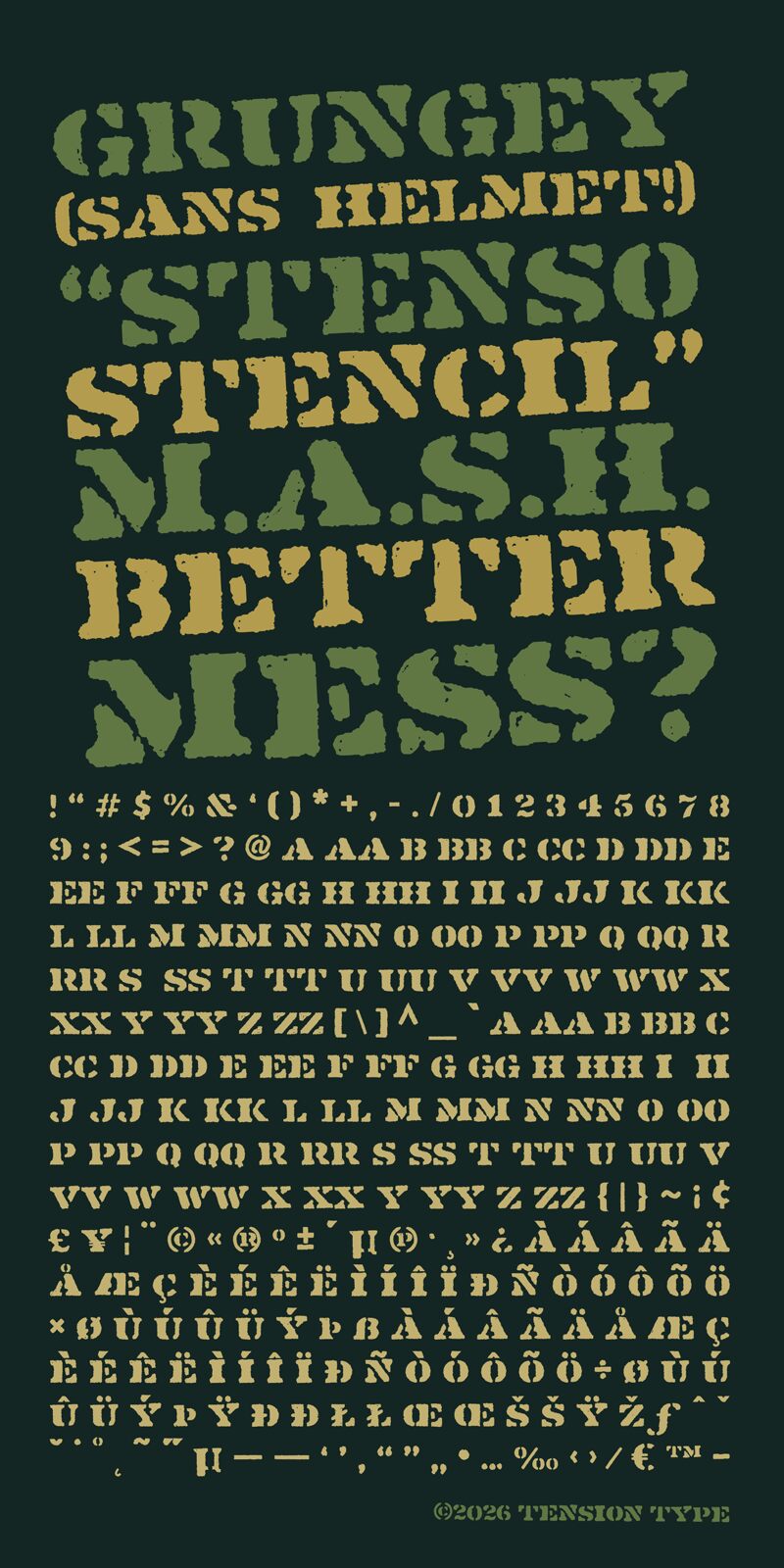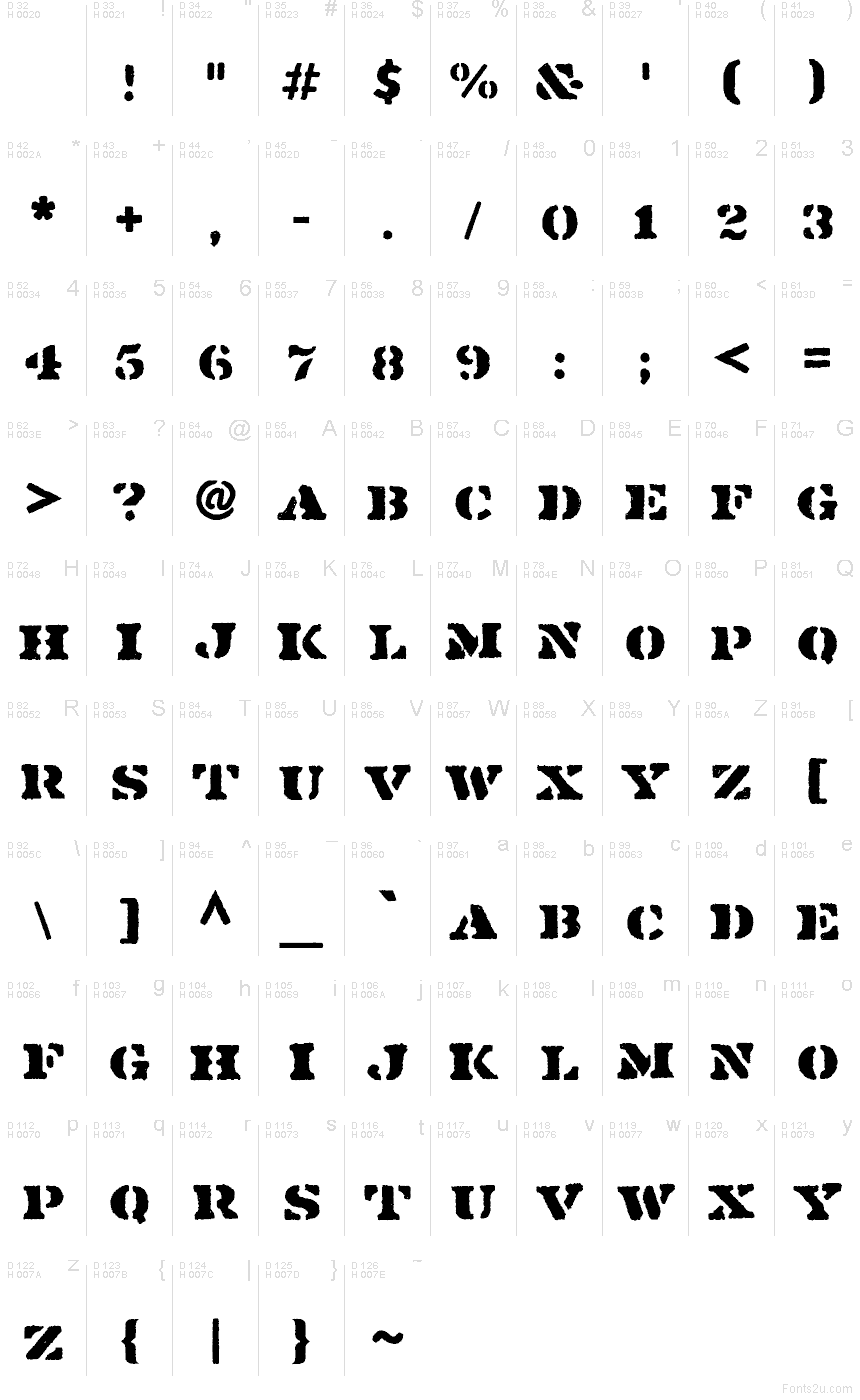
Stenso Stencil Regular
Stenso Stencil è un font display gratuito in stile militare, con un carattere crudo e da campo di battaglia. Le maiuscole appaiono pesanti e vissute piuttosto che costruite in modo pulito, con bordi irregolari, intagli profondi e forme larghe che ricordano quelle stampate su casse, equipaggiamenti o vecchia segnaletica.
Si adatta perfettamente a poster, titoli, packaging, grafiche per eventi e branding per videogiochi in cui il lettering richiede quel mood utilitaristico e militaresco, senza risultare mai troppo levigato. Come font gratuito, è ideale per titoli brevi, copertine e monogrammi, poiché i grossi vuoti dello stencil e la silhouette usurata conferiscono anche a poche lettere l'aspetto di codici o identificativi di unità verniciati.
Questo font è stato creato a partire da un set di lettere vintage Stenso No. 12 del 1956.
Originariamente includeva solo l'alfabeto di base, i numeri e un paio di lettere extra, quindi ho creato io tutti i glifi mancanti.
This was created from a vintage Stenso lettering et No. 12 from 1956. It only had the basic alphabet and numbers a couple extra letters so I created all of the remaining glyphs. It’s rough and organic. Hopefully it’s a fit for your project.